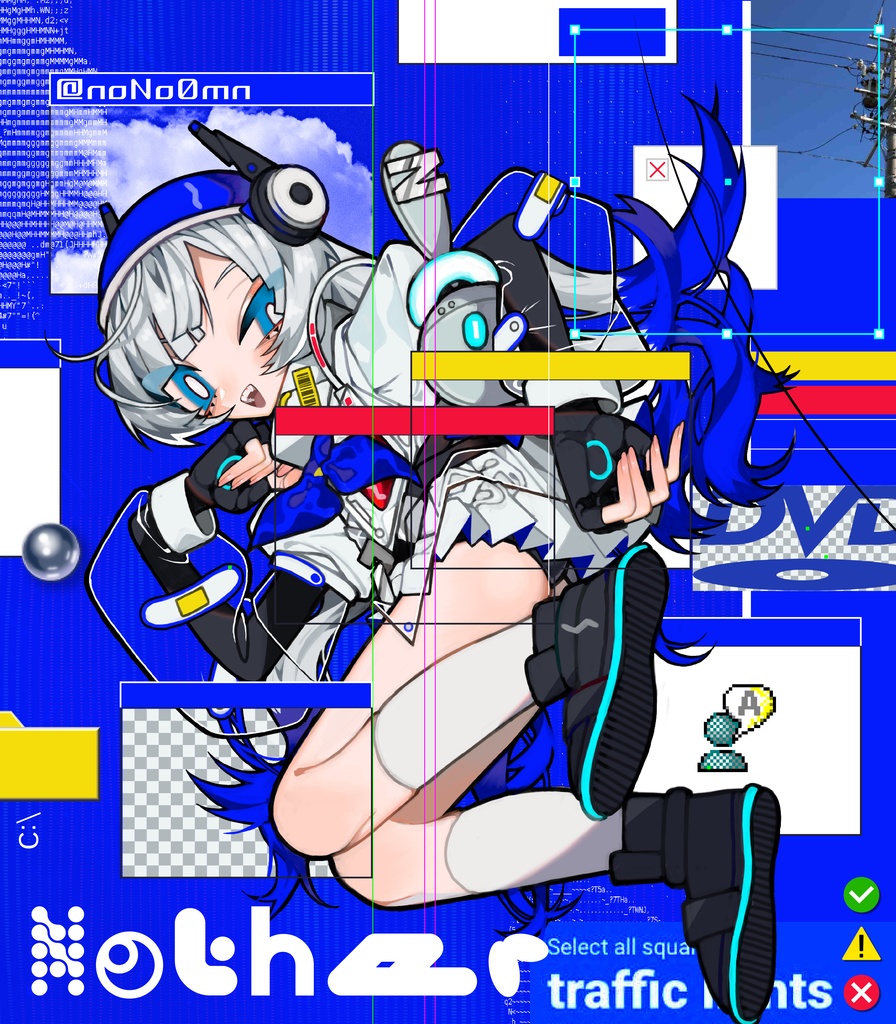
【無料DL企画開催中】✦ Nother✦【頭おかしいなフォント】
📢デザイン📢
このフォントは、Nさんの宇宙人・インタネの要素があったため、Y2K、機械風、SF風など52種類のフォントを作成し、それらを組み合わせ。これにより、電波系でどこか不確かな印象を表現しています。 宣伝画像については、PlayStationゲームディスクのデザインを参考に、Windows 7、クラシックY2K、そして一部のインターネットミームを融合させて作成しました。深く考えすぎず、すべての要素を大胆に盛り込んだ仕上がりです。